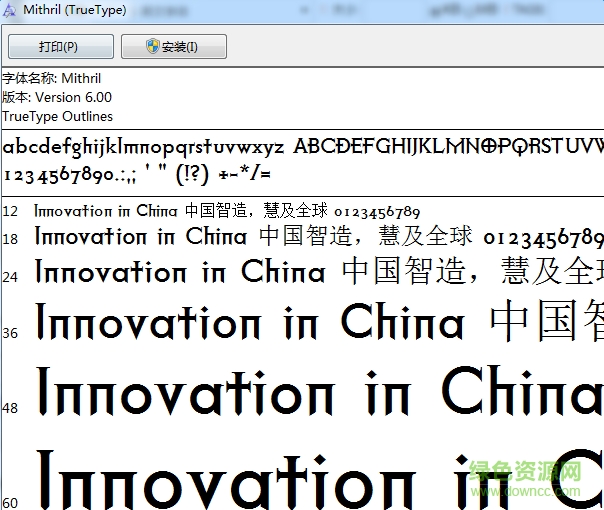
Mithril字體是一款超好用的個性英文字體,該字體可以廣泛應(yīng)用于廣告設(shè)計、宣傳海報、ppt、影視制作以及任何使用文字的領(lǐng)域,有需要的朋友可以免費下載收藏。
Mithril字體是一款極具個性的字體,該字體十分飄逸,彰顯了自己的個性,有喜歡的朋友可以來綠色資源網(wǎng)下載使用!